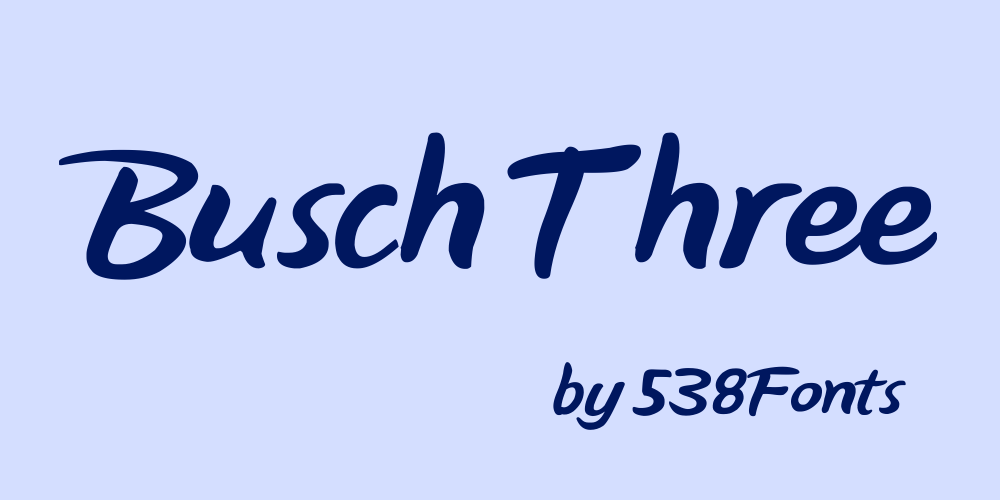
A Busch Three é uma fonte script que surgiu em 2015 no coração da diversidade lingüística brasileira, agora ampliando seu alcance para mais idiomas e caracteres a cada dia. Com a inclusão de mais símbolos e letras ao longo do tempo, a Busch Three se tornou uma fonte versátil que atende as necessidades de designers gráficos de todo o Brasil. Esta fonte é criada pelo designer Hamilton, oferecendo um estilo elegante e fluido ideal para criar texturas sofisticadas em design editorial, logotipos e mídia digital. Seja você um entusiasta da arte ou simplesmente alguém que busca uma solução aprimorada para sua necessidade de fonte, a Busch Three é uma excelente escolha para explorar as infinitas possibilidades criativas que a linguagem pode oferecer.